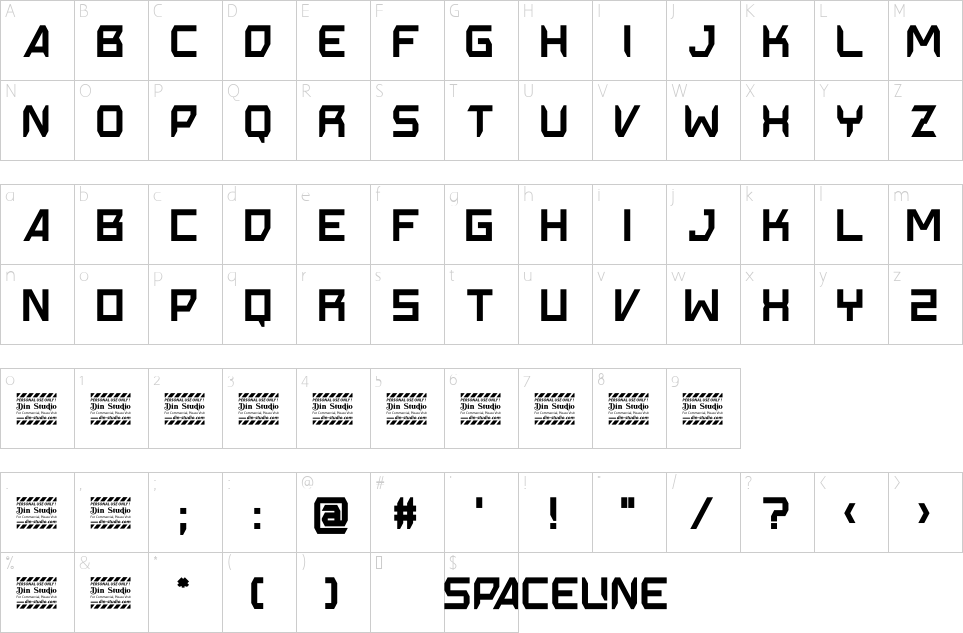
Spaceline Font – Fonte Grátis
Spaceline Font
A fonte Spaceline oferece uma atmosfera futurista e tecnológica para a sua próxima projeto digital, seja ele em seu site ou app. Desenvolvida pela Din Studio, essa elegante tipografia se destacou entre os usuários por sua simplicidade arquitetônica e modernidade minimalista. Com um estilo contemporâneo, Spaceline é perfeito para enriquecer a aparência de seus materiais digitais sem comprometer o design geral do layout. Seu uso no web design ou em aplicativos móveis pode criar uma impressão dinâmica e futurista. Com apenas duas linhas curtas no seu arquivo, Spaceline não apenas ajuda na estilização da sua marca digital, mas também dá um toque de sofisticação que valoriza o seu trabalho. Recomendado para designers gráficos, desenvolvedores front-end ou qualquer pessoa interessada em uma fonte de alta qualidade e moderna sem custos, a fonte Spaceline está disponível para download gratuitamente tanto no Windows quanto no Mac.